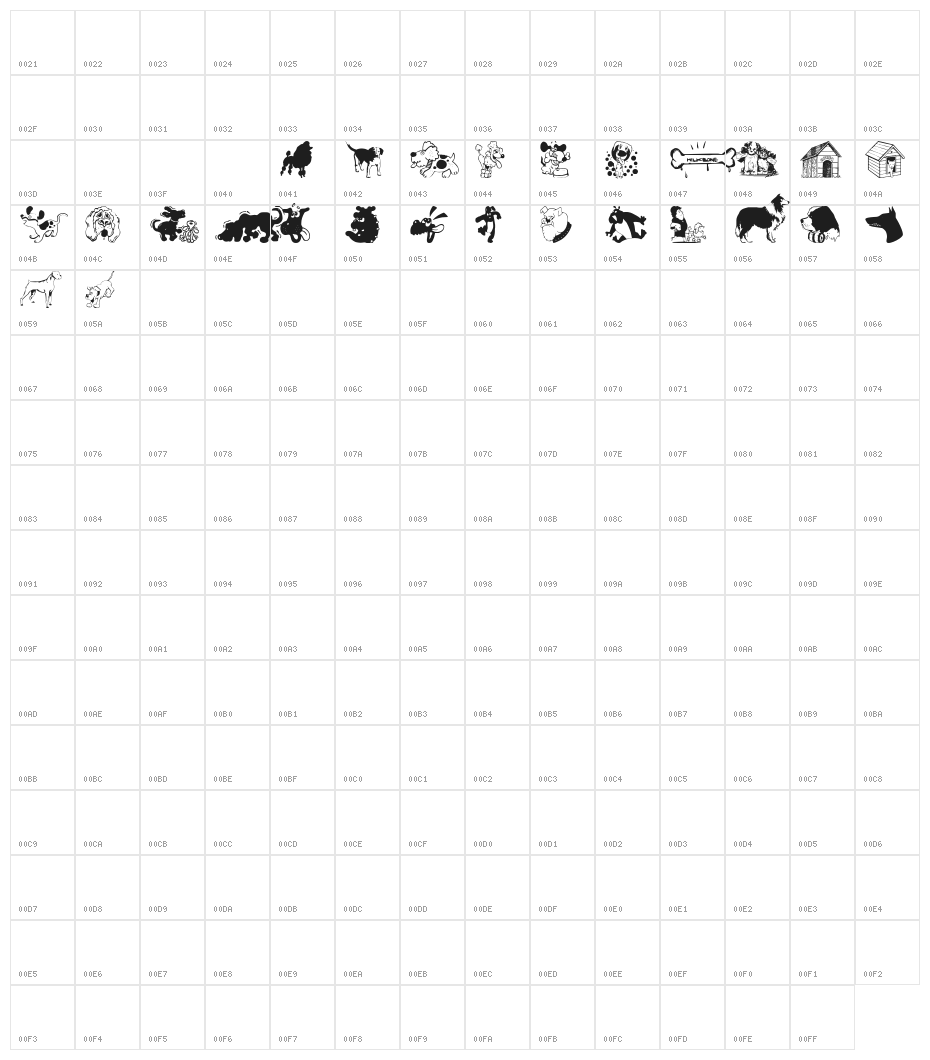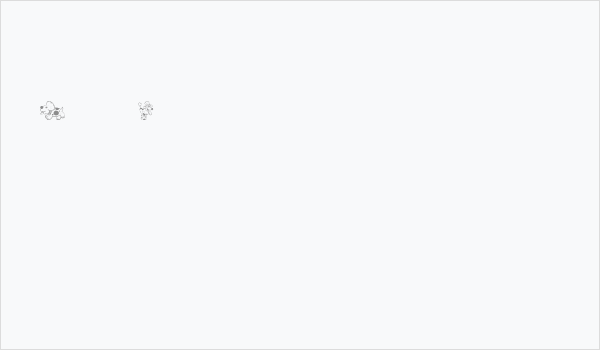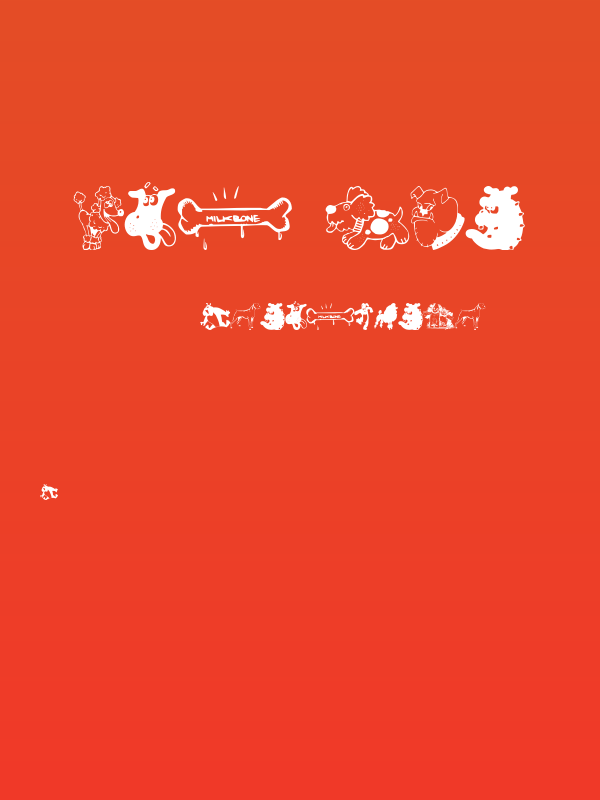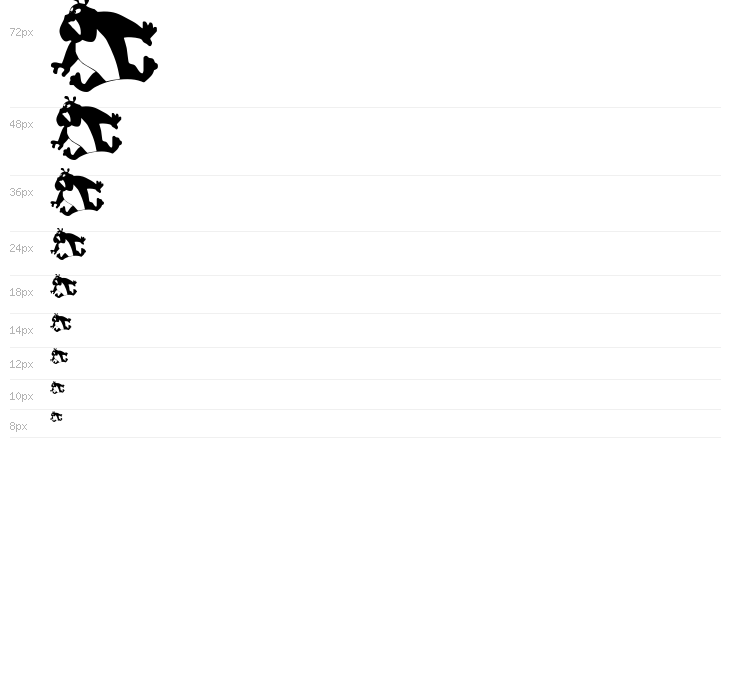
dog_csp Font
| Gesamtstil | Playful, Decorative |
| Anwendungsfall | Logos, Headlines, Themed event materials |
| Vorgeschlagene Projekte | Children’s books, pet shop branding, greeting cards, educational materials, playful posters. |